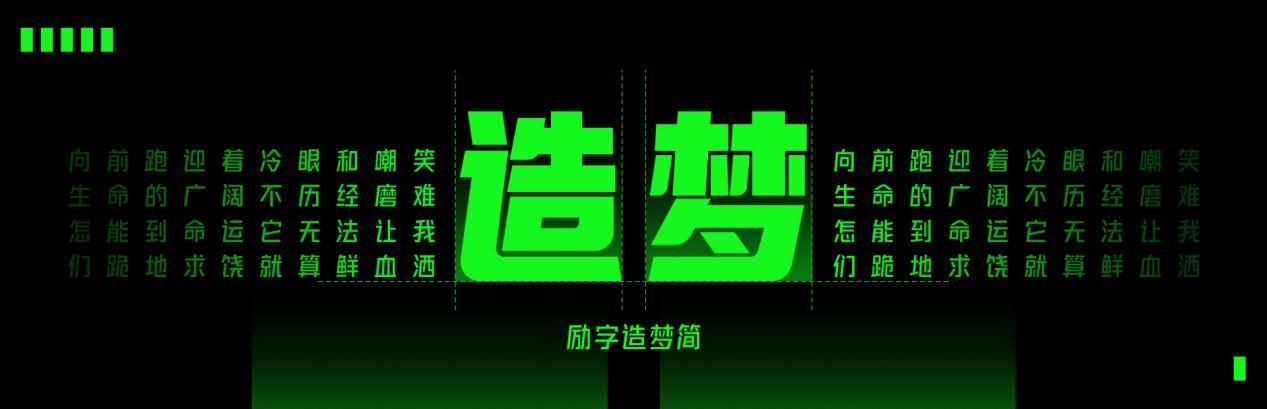
圆梦高考,字造未来,一款跟梦想与青春有关的字体——励字造梦简
追逐梦想的路上,我们身披希望,青春,励字造梦局推荐一款跟梦想与青春有关的字体——励字造梦简,一款现代直线型字体,有力量感,棱角分明,字形轮廓清晰有力。左侧倾斜右侧竖直的不对称设计,夸张的透视感模拟了建筑的宏壮,仿佛在城市之中抬头仰望摩天大厦。